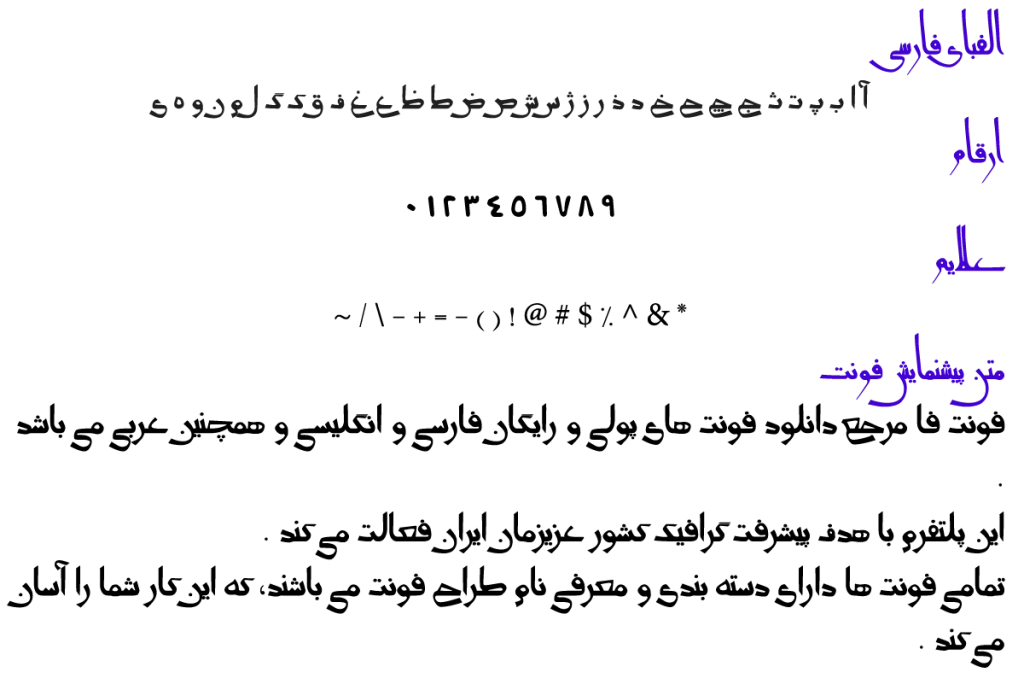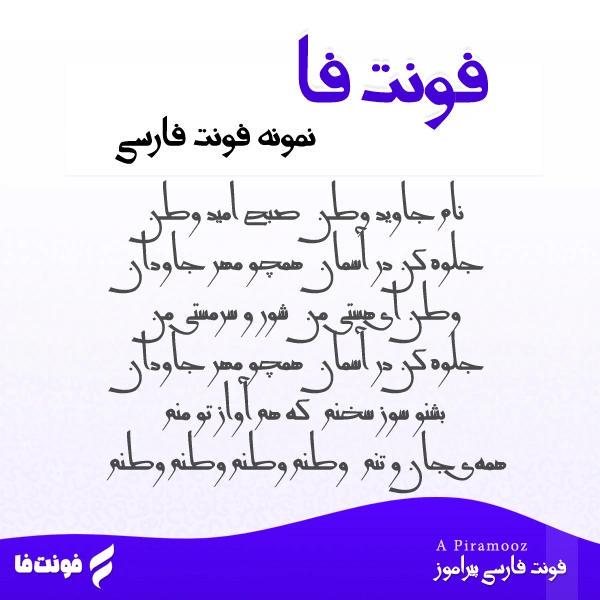
فونت فارسی پیراموز – A Piramooz
طراح فونت: امیر حسین صدقی نوع فونت: فونت فانتزی
پیشنمایش فونت پیراموز
توضیحات و معرفی فونت پیراموز
فونت فارسی پیراموز ( A Piramooz ) از مجموعه فونت های آزاد می باشد، و نیز نوع فونت فانتزی می باشد.
فونت خوشگل مربوط توسط امیر حسین صدقی در سال 1390 طراحی و ساخته شده است.
و نیز فونت A Piramooz در یک وزن پر رنگ است.
در تصویر زیر، شعر کهن «وطنم» با این تایپفیس به نمایش گذاشته شده است.